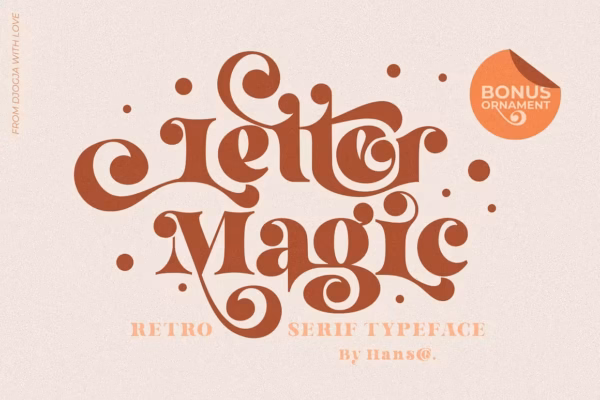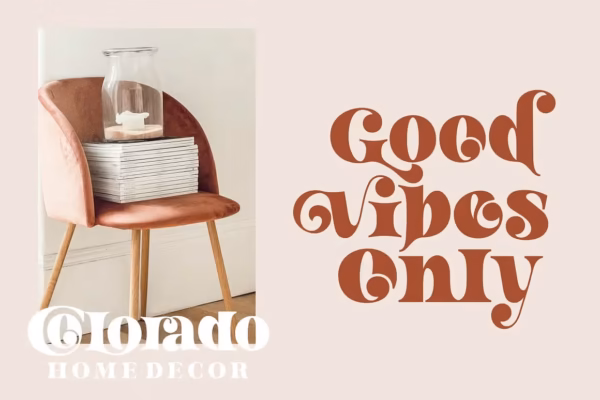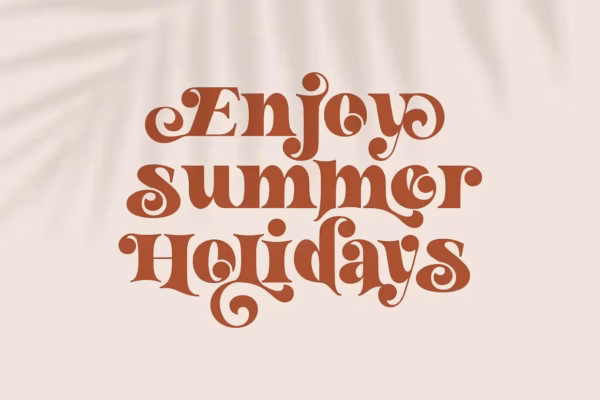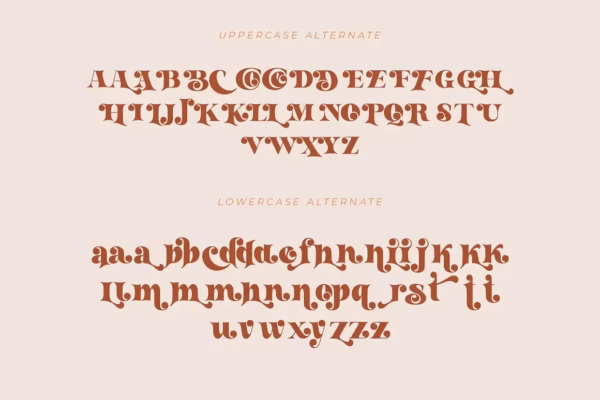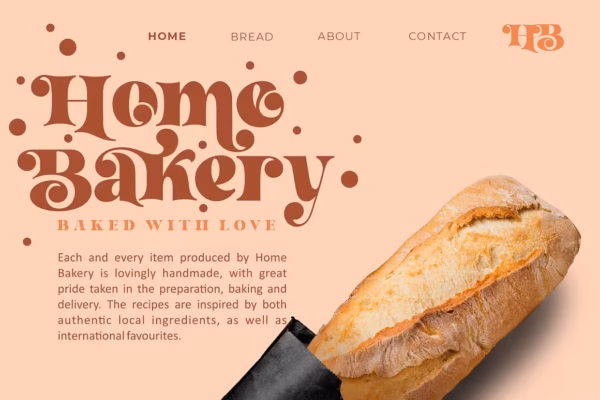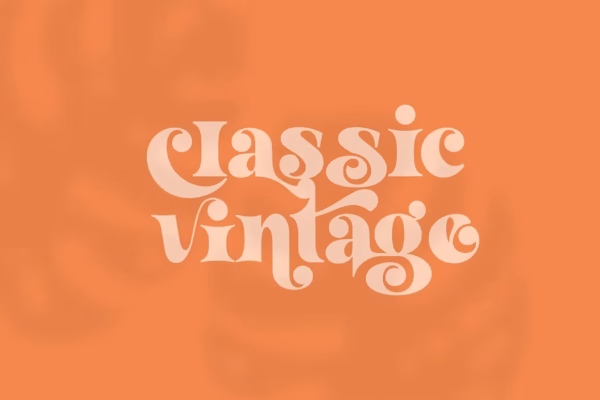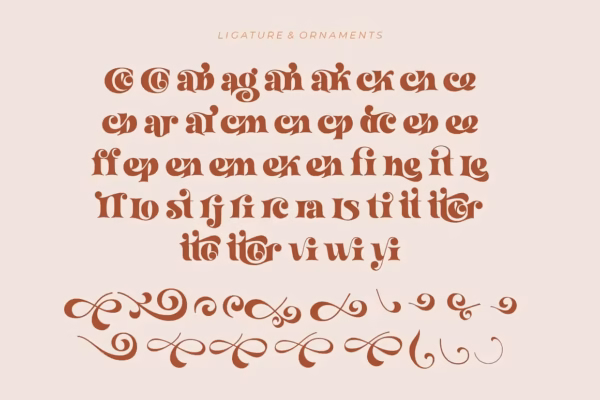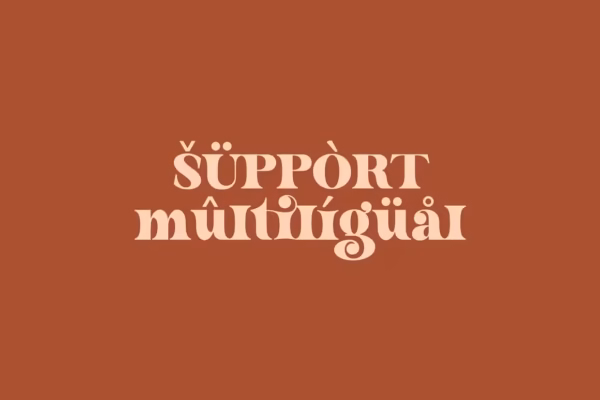
فونت جادوی سریف Retro
این فونت حس نوستالژیک و بازیگوشانهای دارد و یک حال و هوای فوقالعاده وینتیج ایجاد میکند. از این فونت سریف استفاده کنید تا به هر ایده طراحی که در ذهن دارید، یک لمس خاص اضافه کنید!
این فونت با مهارت و دقت طراحی شده تا به یکی از محبوبترین انتخابهای شما تبدیل شود. فونت جادوی سریف Retro این قابلیت را دارد که هر یک از ایدههای خلاقانه شما را به سطحی بالاتر ارتقا دهد.
این فونت دارای کدگذاری PUA است؛ یعنی میتوانید بهراحتی به تمام گلیفها (حروف و نشانههای ویژه) و حالتهای تزئینی آن دسترسی داشته باشید.
ویژگیها:
- حروف بزرگ و کوچک (Uppercase & Lowercase)
- اعداد و علائم نگارشی (Numbers & Punctuation)
- پشتیبانی از زبانهای چندگانه (Multilingual)
- لیگچرها / ترکیبهای ویژه حروف (Ligatures)
- حروف جایگزین (Alternates)
- حروف و تزئینات کشیده (Swashes)
- دارای کدگذاری PUA (PUA Encoded)